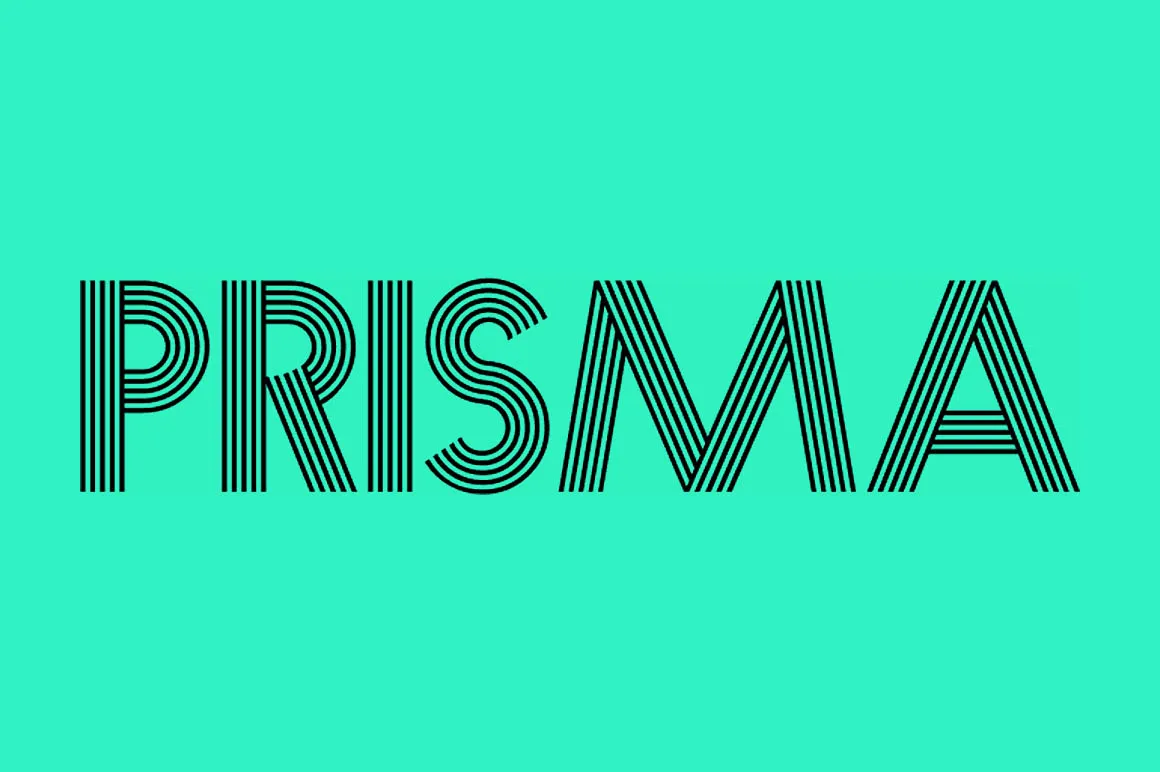
Prisma Font
A fonte ‘Prisma Font’ é uma criação inovadora do designer Hamilton, que traz características geométricas e modernas num estilo totalmente único. Inspirada na obra de Dieter Steffmann, esta fonte sem serif é perfeita para projetos que exigem um tom minimalista e elegante. Suas linhas diretas e clean são ideais para criar identidades visuais modernas ou estilos gráficos contemporâneos, mantendo-se sempre atemporais. A ‘Prisma Font’ se torna uma excelente escolha para designers digitais que buscam um recurso com a capacidade de destacar seus trabalhos e oferecer um toque diferenciado em qualquer projeto.